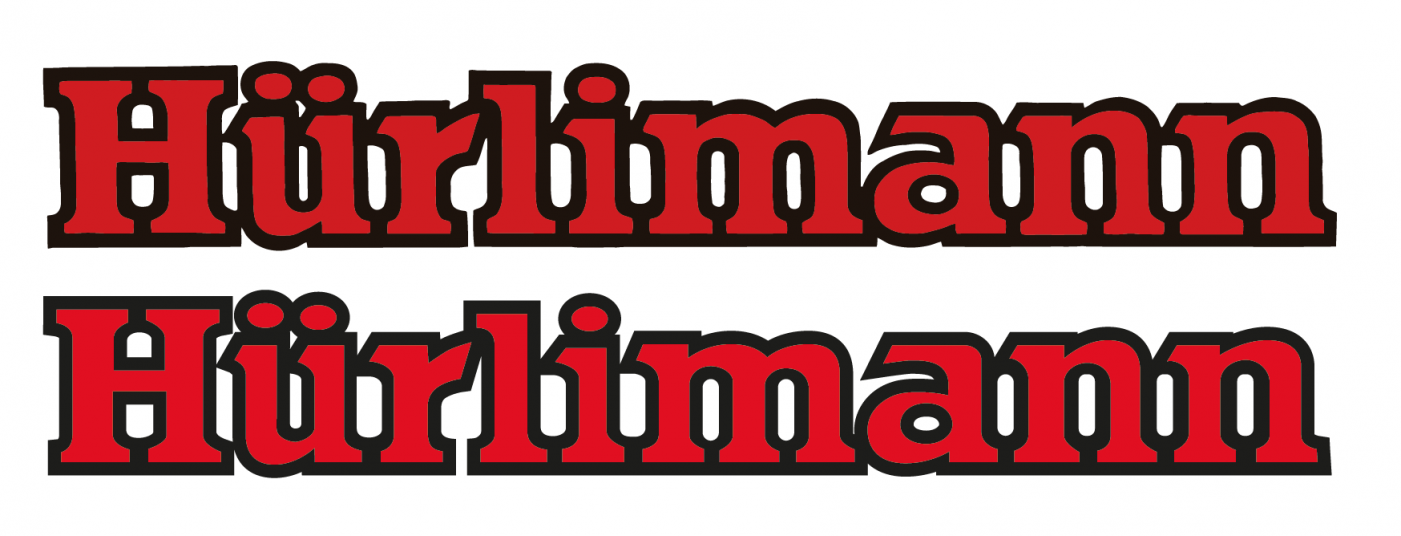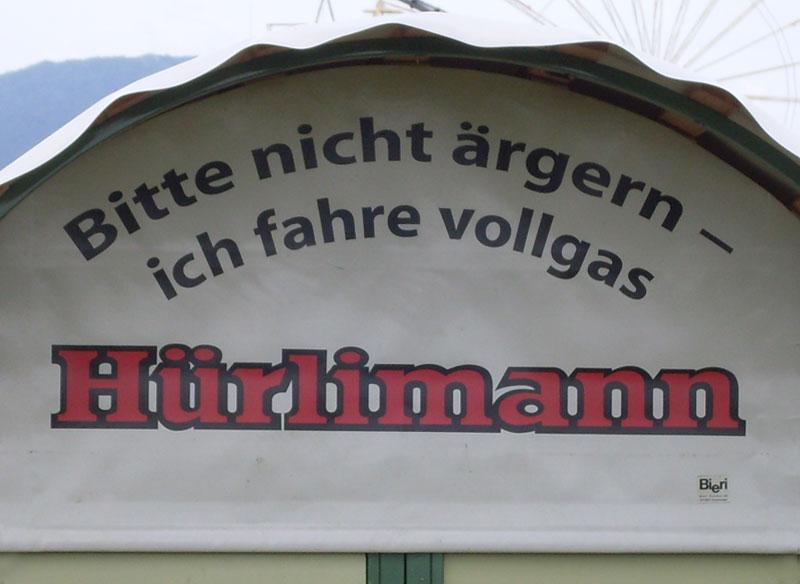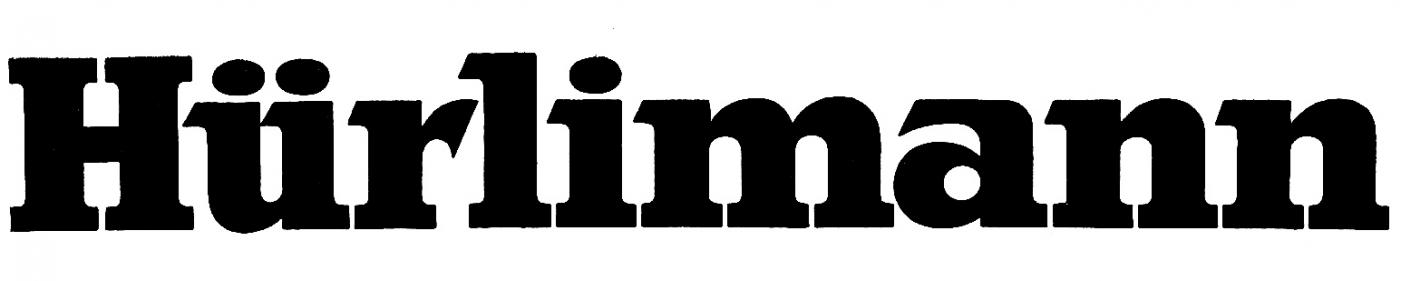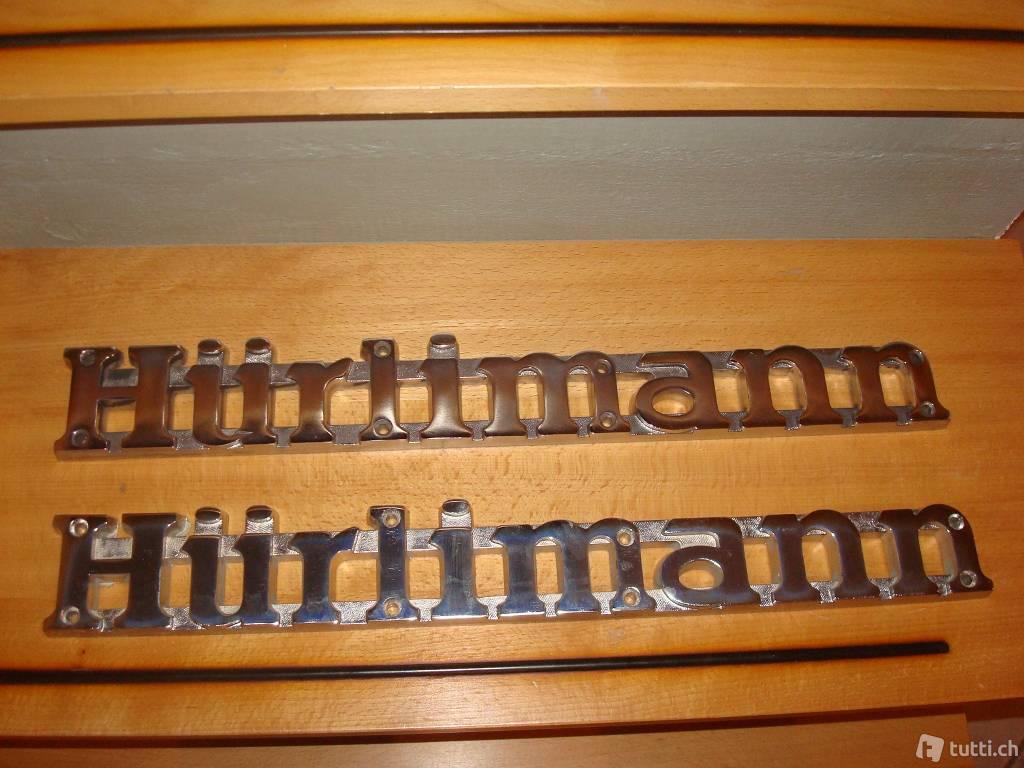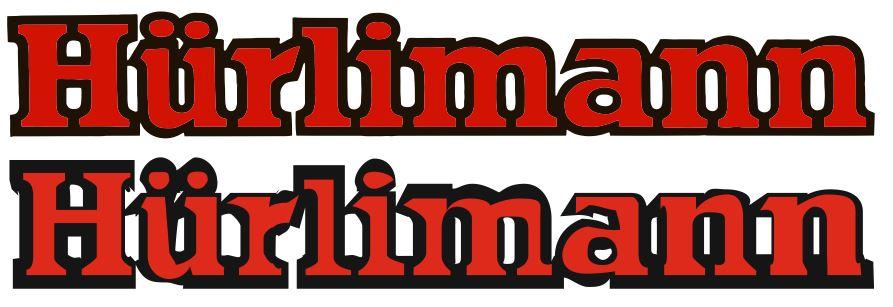
Suche Schrift dieses Hürlimann-Schriftzuges
Ich suche diese Schrift der ehemaligen Hürlimann Traktoren  Werke in der Schweiz.
Ich könnte mir vorstellen das die Schrift aus den 60er Jahren stammt .
Die Bilder habe ich von einer Schweizer Kleinanzeigen Seite .
Ich suche diesen oder ähnlichen Font
Ich möchte die Buchstaben auslasern lassen
Gelöst von RobertMichael
wo könnte ich den Schriftzug hochladen oder hinzufügen ,um vllt ein Ergebniss zu bekommen .
Ich bin leider neu auf dem Gebiet und habe schon zig Website´s durchsucht mit spärlichem Ergebniss .
Könnte man anhand der Form der Buchstaben die Suchfunktion eingrenzen ??
Fakt ist, die Schrift wirst Du so nicht finden.
Damals wurden Schriftzüge zum großteil noch selbst gezeichnet und basieren eher weniger auf bestehenden Schriften. Dieser Artikel erklärt das genauer:
Du könntest nur versuchen eine gute Vorlage zu suchen. Notfalls irgendwo ein Typenschild kaufen und dann jemand hier im Forum (oder einen Grafiker Deiner Wahl) bitten, Dir davon eine digitale Skizze anzufertigen.
Vielleicht kannst Du Dir ja dieses Prospekt: https://www.ebay.de/itm/198622-Hurlimann-H-490-Prospekt-198/392390808389?hash=item5b5c509345:g:rK4AAOSw8fpcwzJE
kaufen und den Schriftzug auf dem Cover digitalisieren, dann kann man diese auch auslasern.
hab was gefunden
Garamond in Fettschrift
Jetzt muss ich nur noch irgendwie  die Buchstaben downloaden und dann kann ich mir den Schriftzug zusammen stellen.
Ich hoffe das funzt   lol
… oder jene:
Vielleicht kann auch jener Sammler weiterhelfen:
Die sind ja meist gut vernetzt und kennen immer irgendjemanden, der jemand kennt, der das schon digital hat …
auf der Seite steht das es Garamond in Fettschrift sein soll .
Da ich nicht so die Ahnung habe wo ich die Schrift herbekommen bzw runterladen soll,  bitte ich doch mal jemanden nur das H hier von Garamond in Fettschrift darzustellen, um zusehen ob ich damit was anfangen kann .
aber das was du stück weiter oben (rot/schwarz) gepostest hast gefällt mir besser .
Am Dienstag hab ich einen Termin ,ich wollt paar Aufkleber machen lassen .
Mal schauen ob er was mit der Rot/Schwarzen Schrift anfangen kann .
Vielleicht kann er Sie digitalisieren lassen .
Vielleicht passt dir ja schon diese halbautomatische Digitalisierung:
das sieht doch seeehr gut aus .
Montag oder Dienstag weiß ich mehr ob es funktioniert .
Was macht sie brauchbarer?
Hier ein Vergleich: Oben deine, unten meine, Screenshot aus Adobe Illustrator